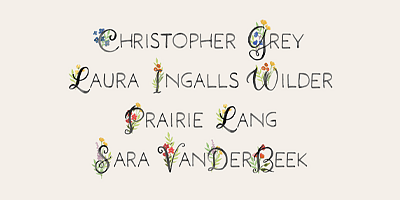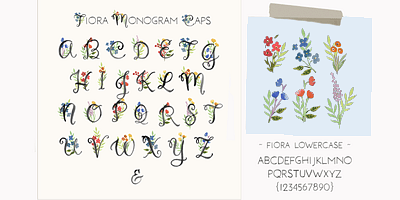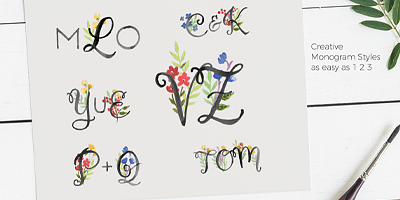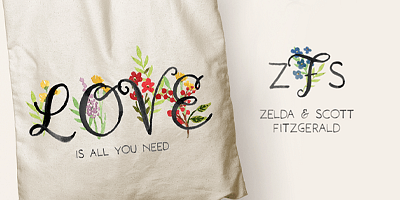
Fiora Monograms は、フルカラーの甘い手描きのモノグラムフォントです。大文字には、モノグラムとドロップ キャップ用にデザインされた装飾的な花柄のキャップが含まれています。小文字は、すべて大文字の水彩文字で構成され、完全な句読点とヨーロッパ言語のサポートにより、フォントを他のテキストアプリケーションで使用できます。Fiora は文房具やプロダクトに適しています。
孤立した花のアイコンは、代替数字グリフやグリフチャートとしてアクセスできます。モノグラミングのアイデアについては、ポスターをご覧ください。